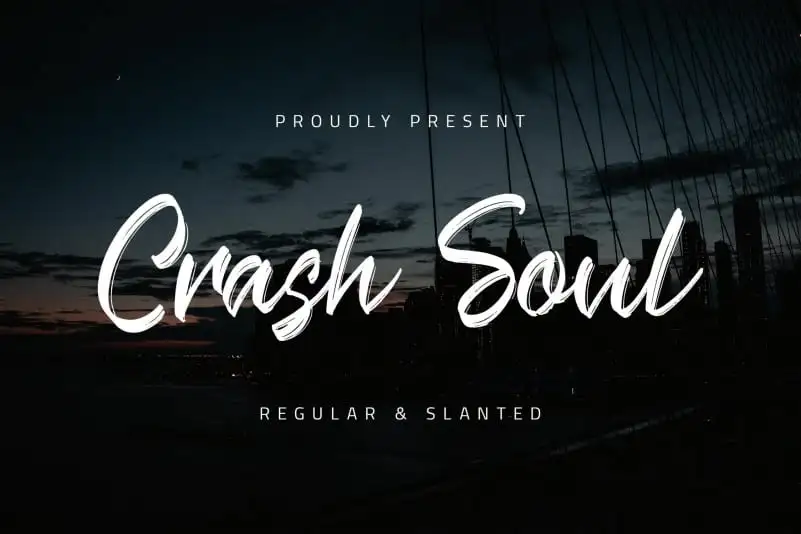
Crash Soul Brush Font – Download Grátis
Descubra a Crash Soul Brush Font, uma novidade inspirada no estilo da caligrafia com báscula. Esta fonte script é perfeita para quem busca algo divertido e autêntico para aplicar em designs de superfície como móveis de casa, criação de marcas, logos ou embalagens de produtos. A Crash Soul se destaca por seu aspecto natural, com letras criadas com básculas sobre papel, depois digitalizadas e desenhadas novamente em formato vetorial. Essa característica torna o texto mais autêntico e relaxado, oferecendo uma aparência mais natural aos seus designs. Você pode explorar ainda mais a paleta de ligaturas OpenType para criar combinações única e interessantes. A Crash Soul é ideal para todos os projetos que valorizam um toque moderno e elegante ao mesmo tempo em seu design.